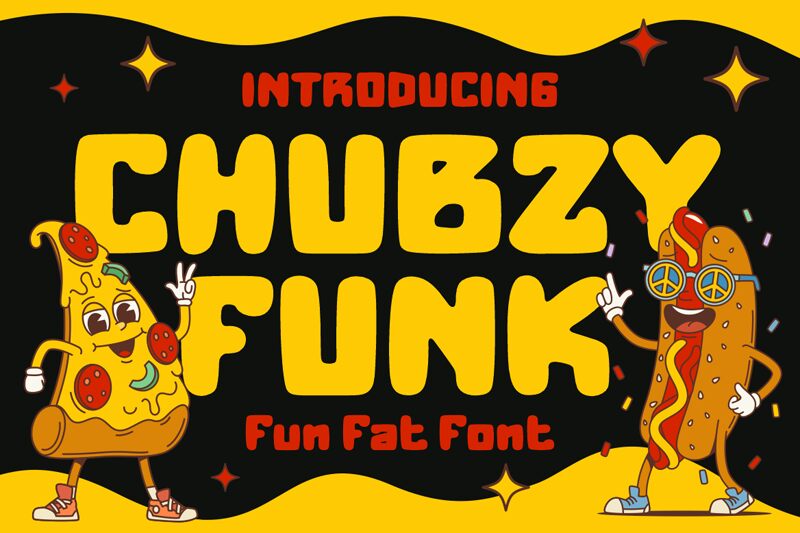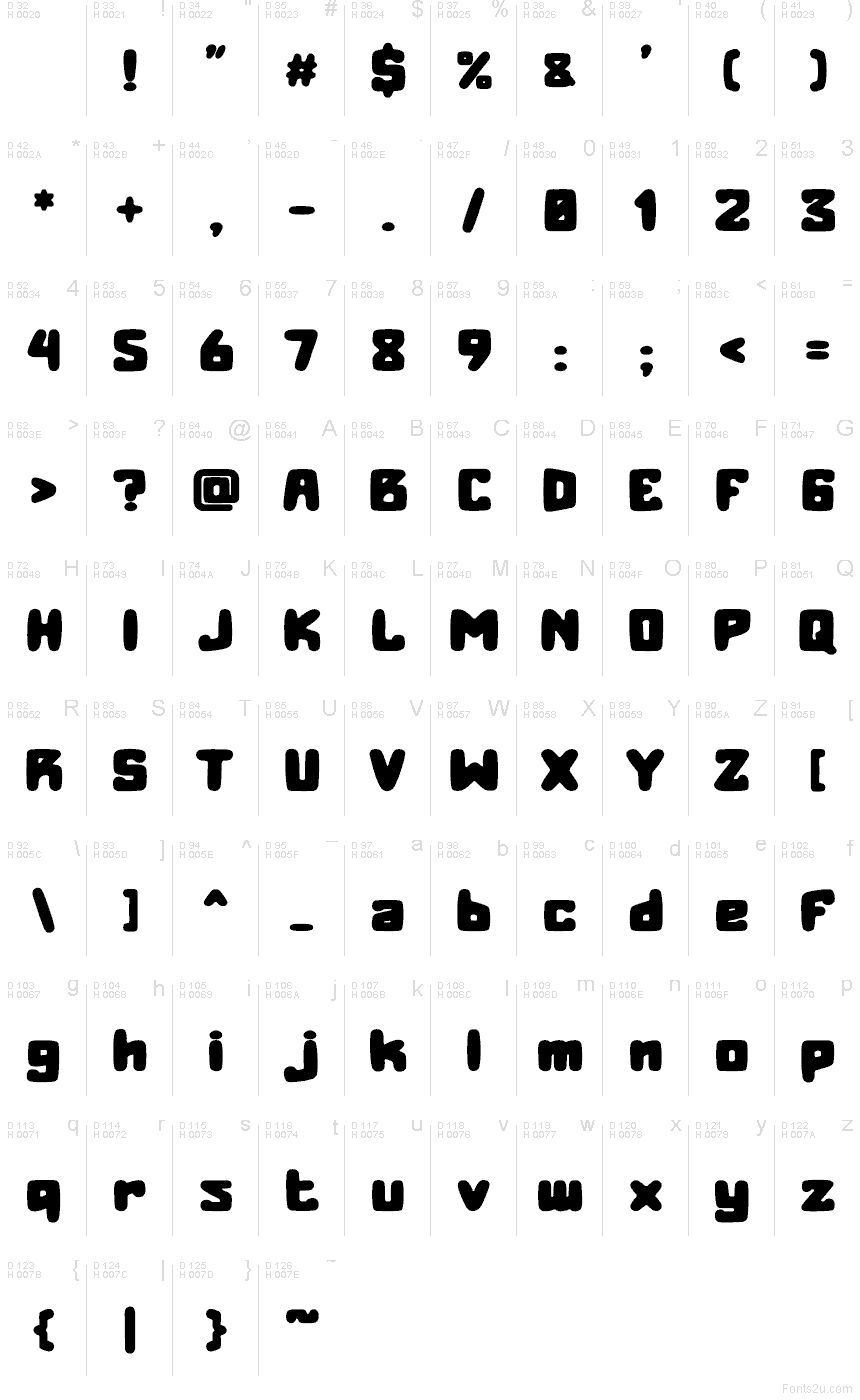
Chubzy Funk de Shanaf Studio es una tipografía tipo display gratuita de estilo cartoon, con ese toque retro-pop tan animado. Sus letras se sienten suaves y gorditas, con formas redondeadas y robustas, espacios internos estrechos y un ritmo ligeramente irregular que hace que la tipografía sea divertida y llena de personalidad.
Es perfecta para empaques de dulces, portadas de libros infantiles, diseño de stickers, miniaturas de YouTube y trabajos de logotipos cortos en los que el texto necesite una voz graciosa y simpática. Al ser gratuita, también es ideal para invitaciones a fiestas, tarjetas de título y publicaciones llamativas en redes sociales, especialmente en líneas cortas donde esas formas rellenas pueden destacar por sí mismas.